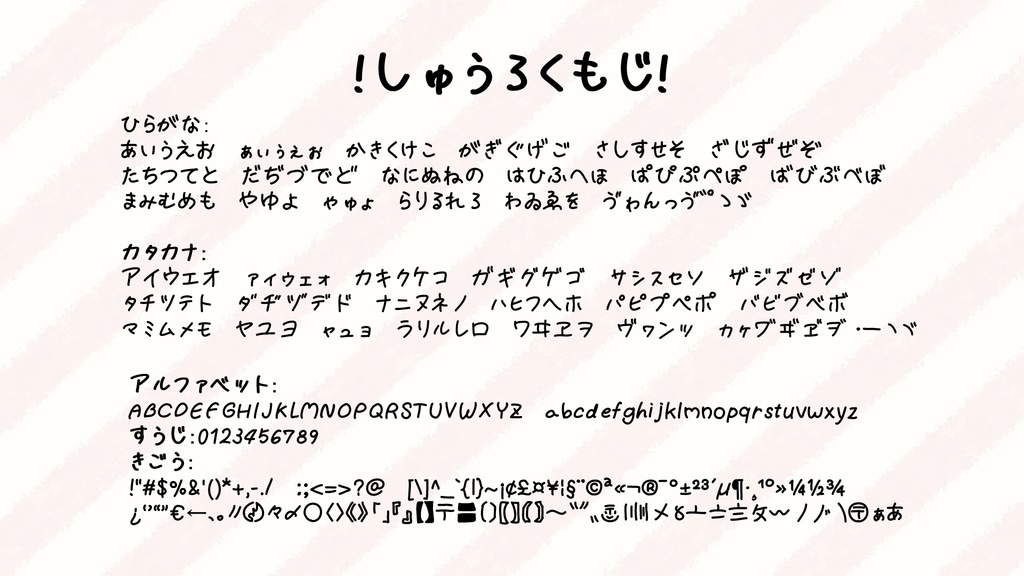
【フリーフォント】そし太マル
アプリiFontMakerで制作した手書きフォントです。 英数字と一部記号に対応。 (2023.02.14追記) ひらがなとカタカナに対応しました。 【ファイル内容】 ・TrueType形式データ ・OpenType形式データ ・Readme ・収録文字一覧(PDF) 【利用に関して】 ▼商用•非商用での利用が可能です。 クレジット表記は任意です。 ▼禁止事項 •自作発言 •二次配布 •誹謗中傷目的、公序良俗に反する場面での使用 ▼著作権は放棄していません。 テスト投稿なので突発的に削除するかもしれません。 何かあればこちらまで Twitter:@ss_noonly Googlefoam:https://forms.gle/x98KupCfeCZVd5xt5